VSCodeにははじめから見やすいフォントが入っていますが、コードを書く時間が長くなるほど、フォントの違いが効いてきます。0(ゼロ)とO(オー)の見分けやすさ、l(エル)と1(イチ)とI(アイ)の見分けやすさ、=>のような記号がひとつながりの矢印になる「リガチャ」、そして日本語のコメントの見えかたまで——コーディング専用フォントは、コードを読み書きすることだけを考えて作られています。ここでは無料で使えるおすすめを、タイプ別に見本つきで紹介します。
}日本語との相性がいい(コメントまで同じ書体)
英字だけのフォントは、日本語のコメントになった瞬間だけ書体がガラッと変わります。ここで紹介する5つは日本語の文字も自前で持っているので、英字と日本語が同じ書体でそろいます。
Source Han Code JP
Adobeが作った、日本語コーディングフォントの本家。英字のSource Code Proと、日本語のSource Han Sans(Noto Sans CJKと同じ設計)を組み合わせています。迷ったらこれ。
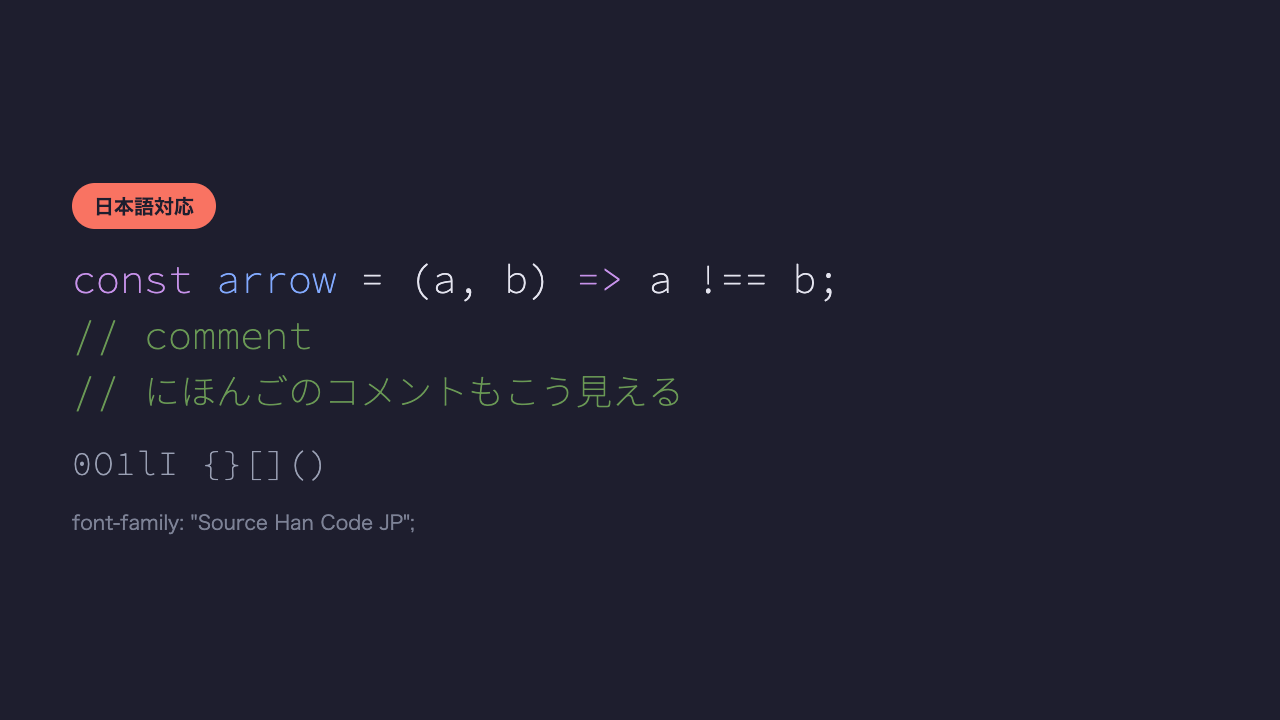
PlemolJP
IBM Plex MonoとIBM Plex Sans JPを組み合わせた、活発にアップデートが続く人気フォント。半角と全角の幅の比率が1対2で、タブでの整列もしやすい設計。
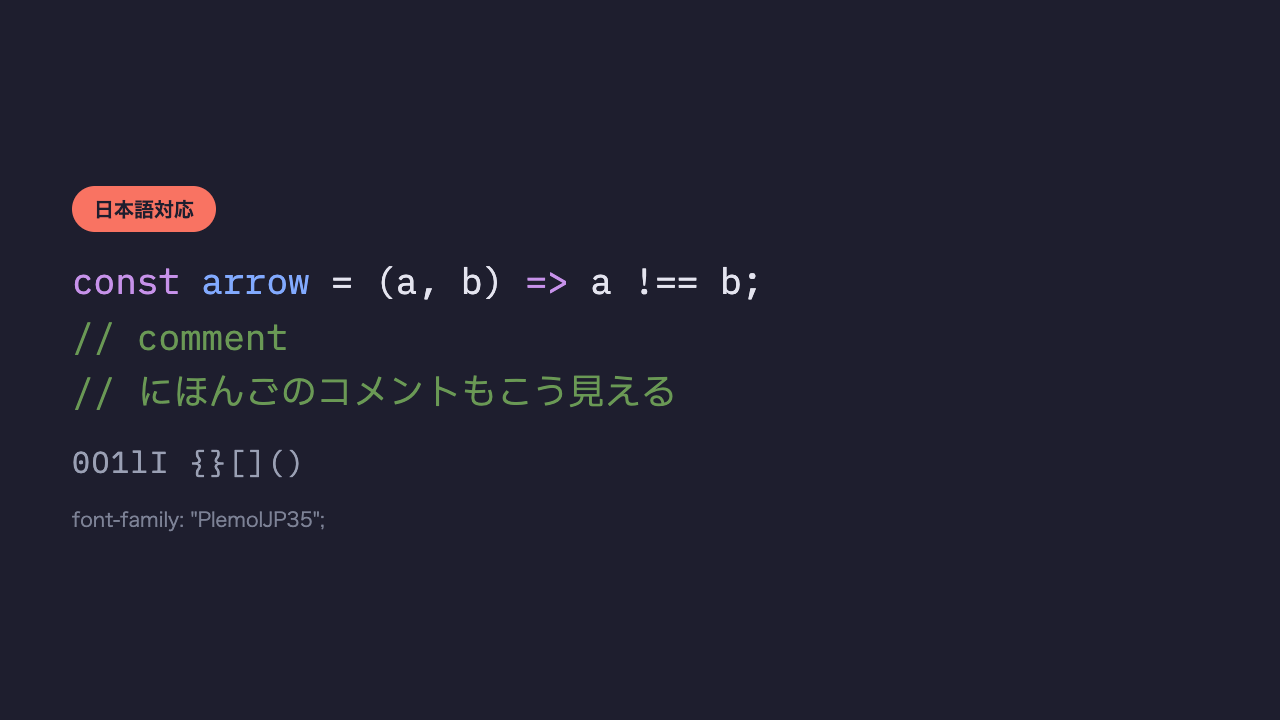
Moralerspace Neon
Monaspaceと日本語フォントを組み合わせた、比較的新しい日本語コーディングフォント。Monaspace譲りの「texture healing」で、字づまりのバランスも整えてくれます。
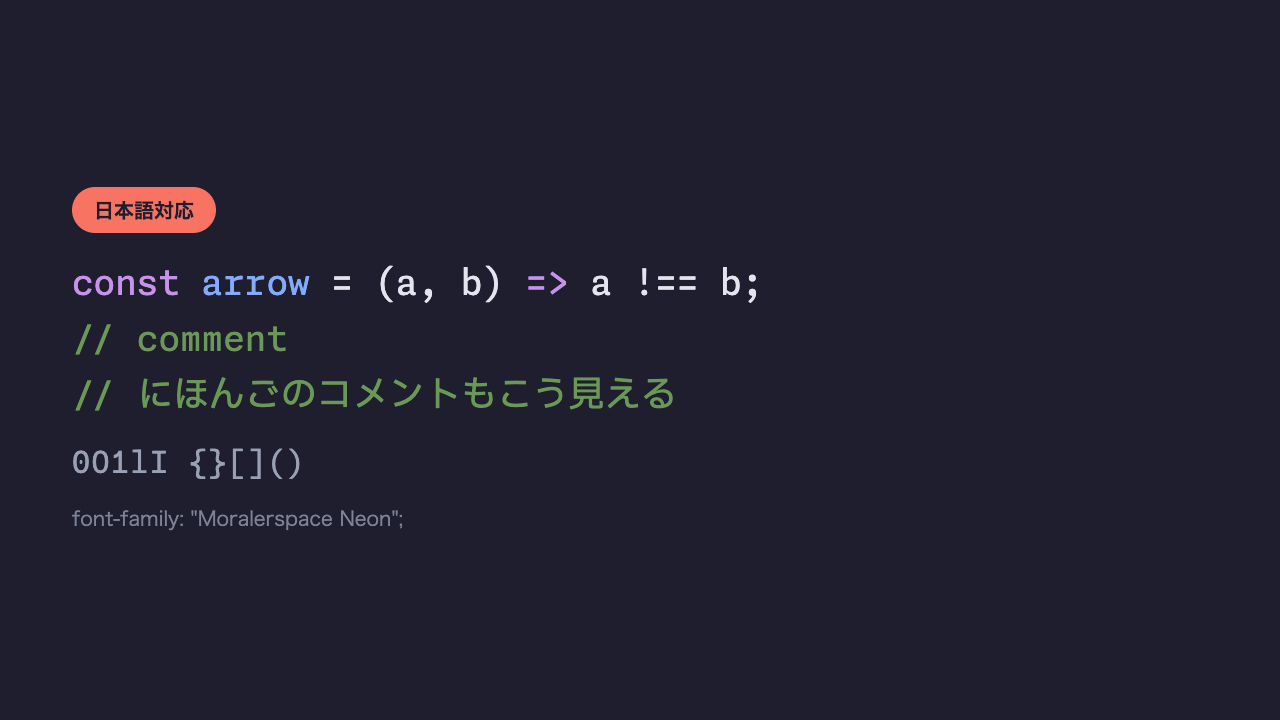
UDEV Gothic 35NF
Cascadia CodeベースのラテンとBIZ UDゴシックベースの日本語を組み合わせた、日本語コーディングフォントの人気どころ。「35」は英字と日本語の幅の比率をあらわしています。
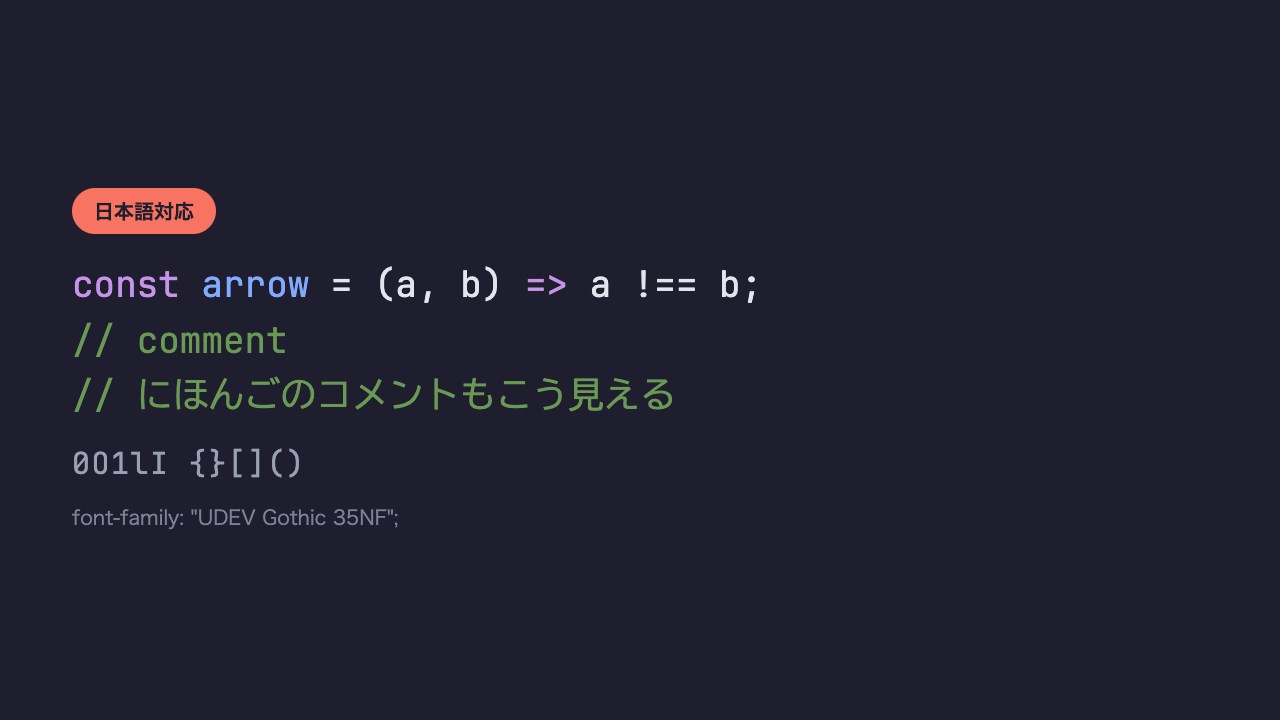
HackGen35
定番コーディングフォント「Hack」と、日本語ゴシック「源柔ゴシック」を組み合わせたフォント。UDEV Gothicと同じ作者による、もうひとつの人気どころ。
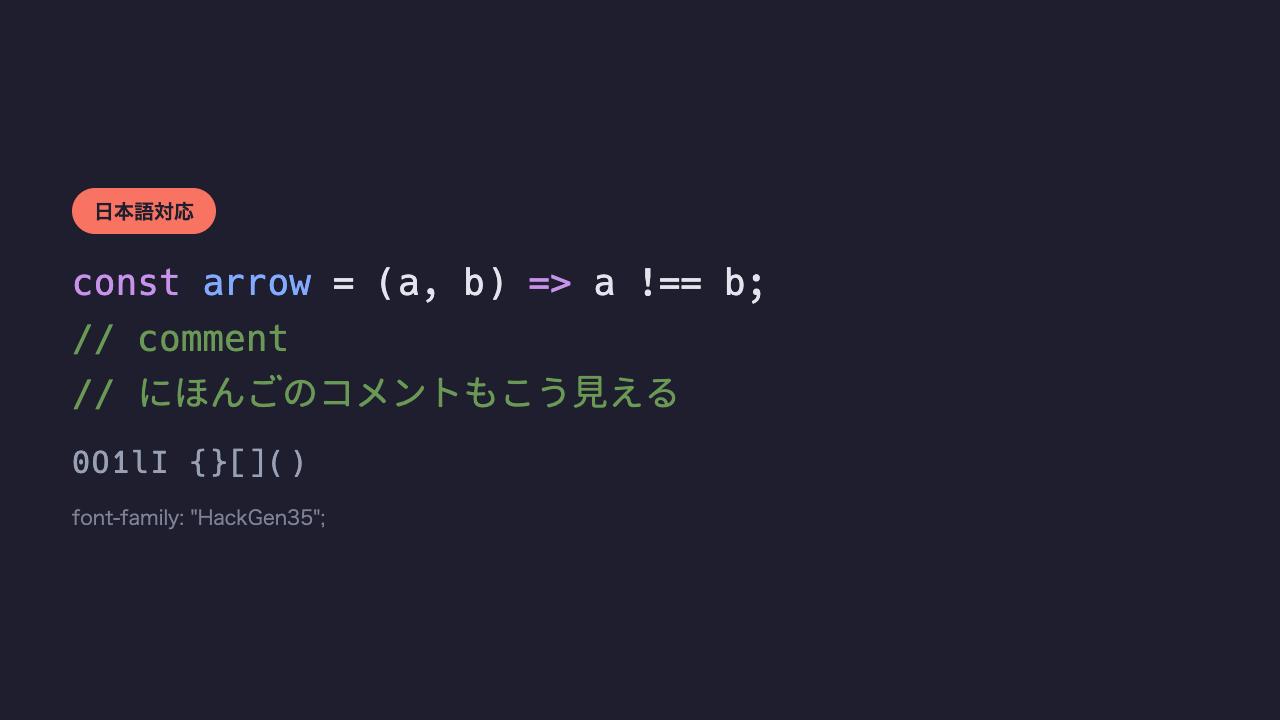
定番・読みやすさ重視
かざりの少ない、王道のコーディングフォント。長時間コードを読んでも疲れにくいことを重視して作られています。
JetBrains Mono
JetBrains社が「開発者の目の負担を減らす」目的で設計したフォント。文字の高さがそろっていて、行が詰まって見えにくくなりにくいのが特徴。
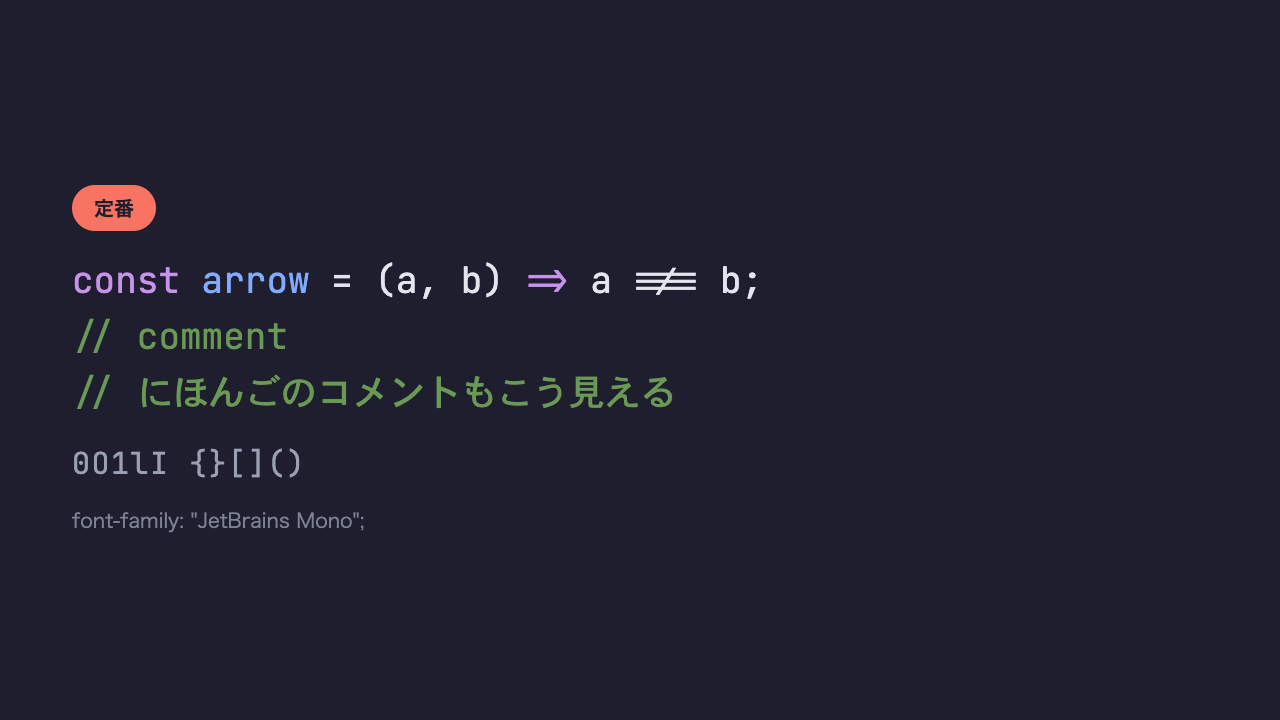
=>や!==がひとつながりの記号になっている、リガチャ入りの見本です。迷ったらまずこれ。Source Code Pro
Adobeが作った、コーディングフォントの古典。クセがなく、どんなエディタ・テーマにもなじみます。
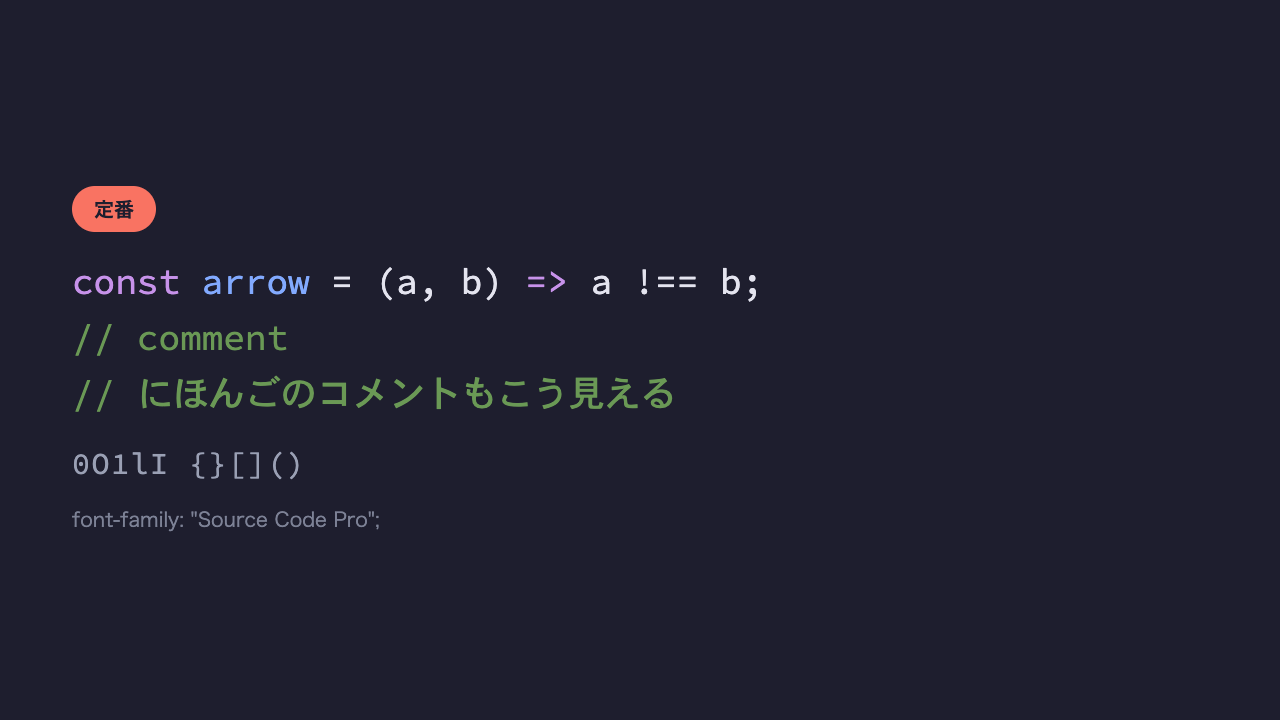
Cascadia Code
Microsoftが作り、VSCodeやWindows Terminalに標準で同梱されているフォント。すでにインストール済みという人も多いはず。
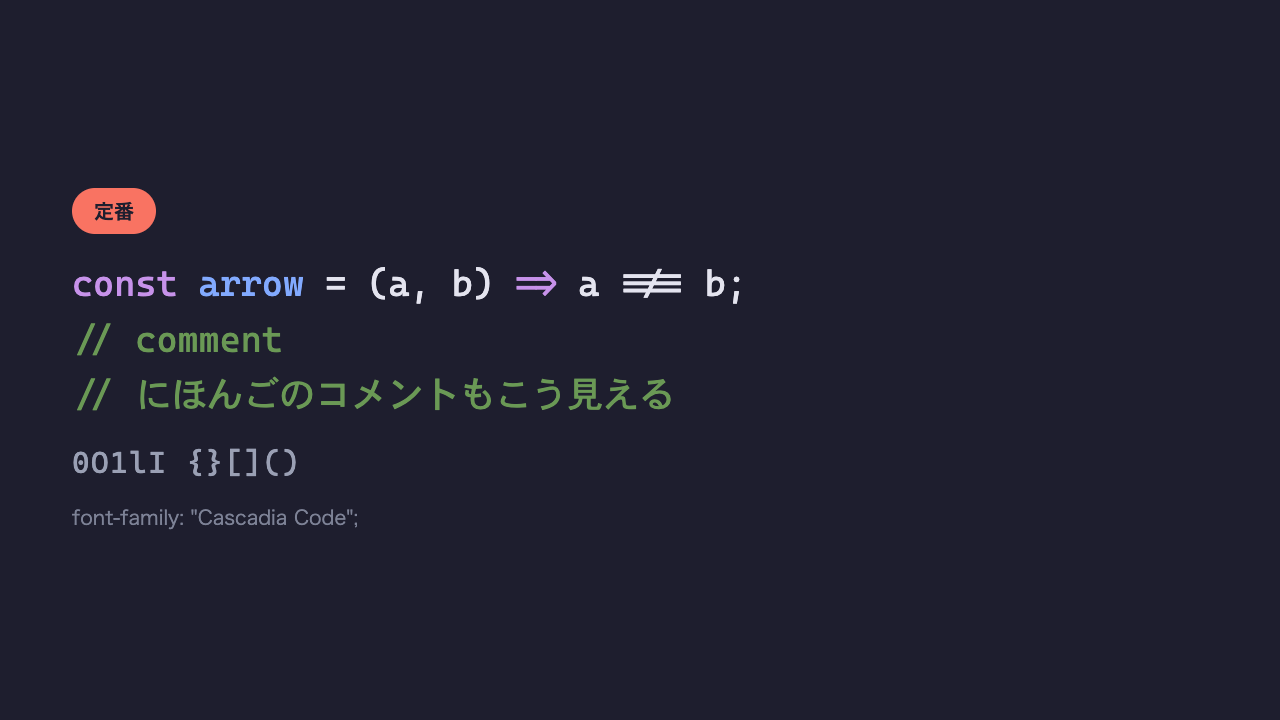
Roboto Mono
Googleが作った、Robotoファミリーの等幅版。Android・Chromeまわりでもおなじみの、まっすぐで力強い印象。
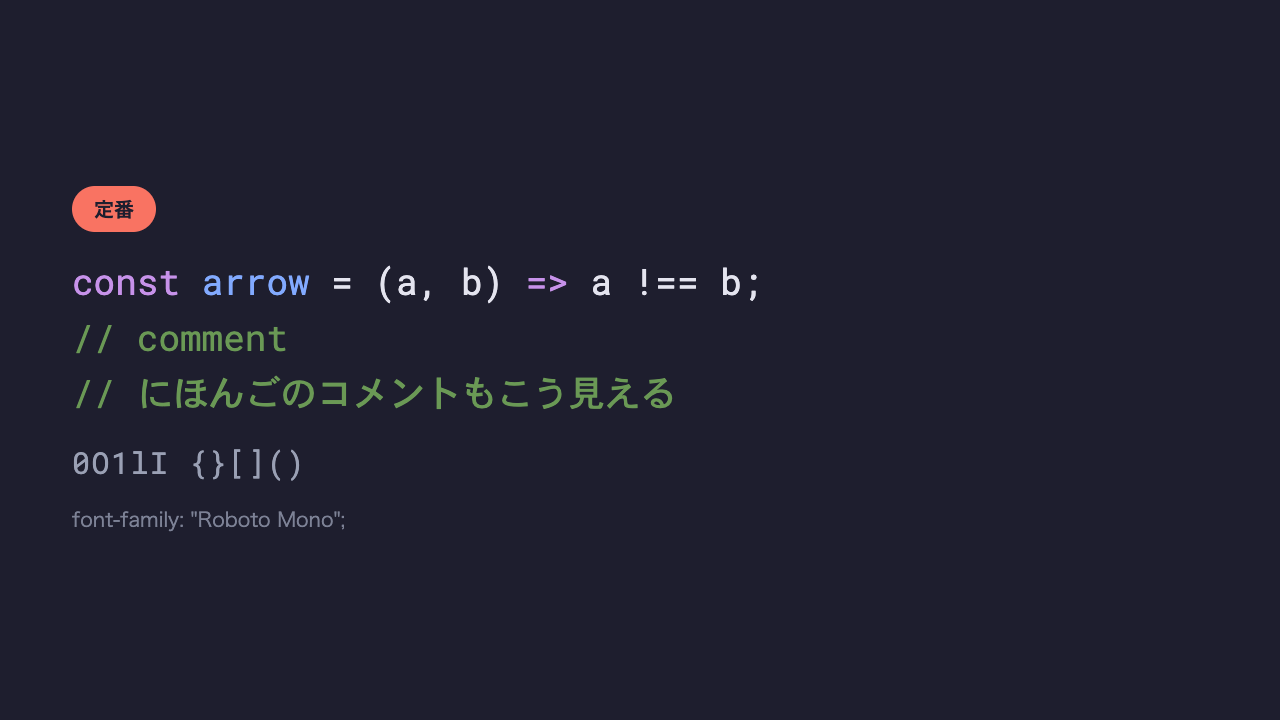
Inconsolata
コーディングフォント界隈で長く愛されてきた、細身で上品なミニマルタイプ。
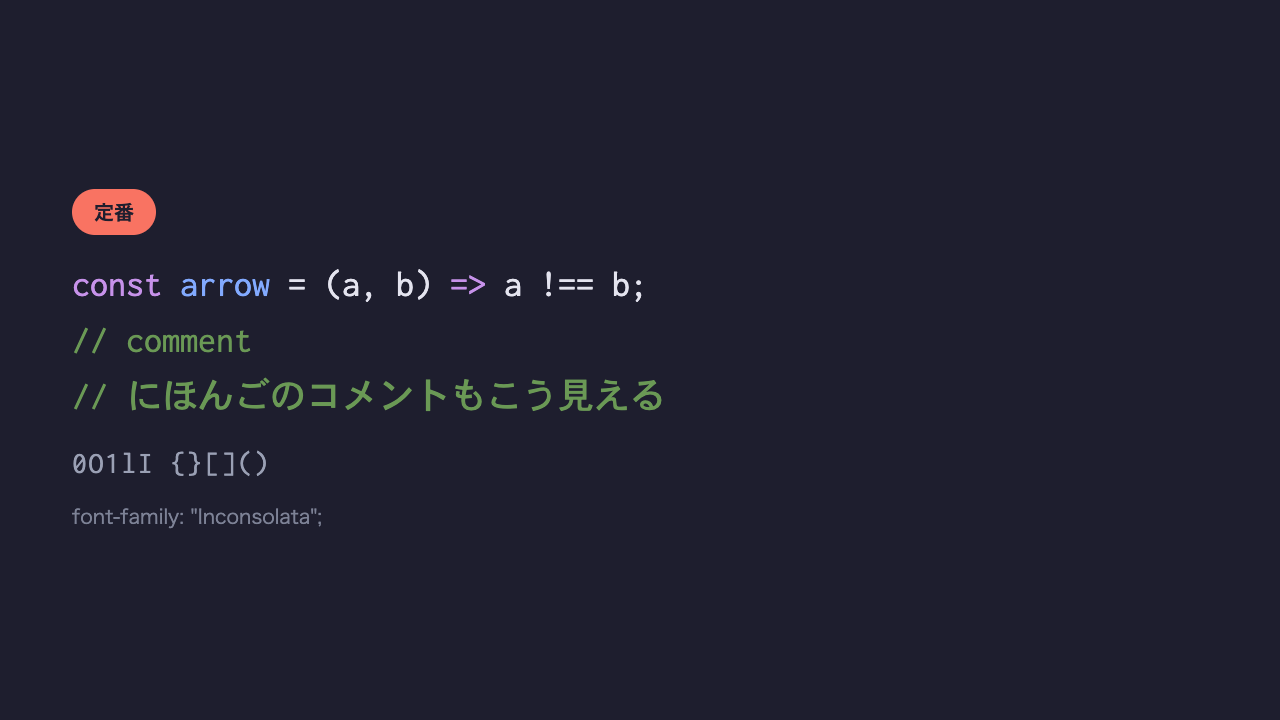
リガチャ(合字)で記号がキマる
=>や!==のような複数の記号が、ひとつながりの形に合体して表示される機能がリガチャ。コードの意味が記号の形でぱっと伝わるようになります。
Fira Code
リガチャ入りコーディングフォントの火付け役。矢印やイコールの合字がとても自然な形をしています。
Victor Mono
リガチャに加えて、コメント部分を筆記体のようなイタリック体で表示できるのが最大の個性。
ちょっと個性を出したい
読みやすさは保ちつつ、文字の形に個性があるタイプ。エディタを開くたびに気分が上がります。
IBM Plex Mono
IBMのブランドフォント一族の等幅版。角がやわらかく、モダンで上品な印象。
Space Mono
タイプライターのような、レトロで武骨な等幅フォント。数字の0にスラッシュが入り見分けやすい。
Monaspace Neon
GitHubが開発した、比較的新しいコーディングフォント一族。5つの書体を混ぜて使う「texture healing」という仕組みが特徴で、Neonはその中でもクセの少ない主力タイプ。
Iosevka
驚くほど文字幅がスリムな、縦長のコーディングフォント。カスタマイズの幅も広く、自分好みの太さ・幅に調整して使う人も多い一族。
Anonymous Pro
その名の通り、匿名性のあるそっけない見た目の等幅フォント。昔ながらのターミナルらしい、飾らない雰囲気。
まとめ
- コーディング用フォントは、Webページ用のフォントとは別物。
0とOの見分けやすさなど、コードを読み書きすることだけを考えて作られている - 迷ったら定番のJetBrains Mono、記号の合字を楽しみたいならFira Code、日本語コメントまで書体をそろえたいならSource Han Code JP